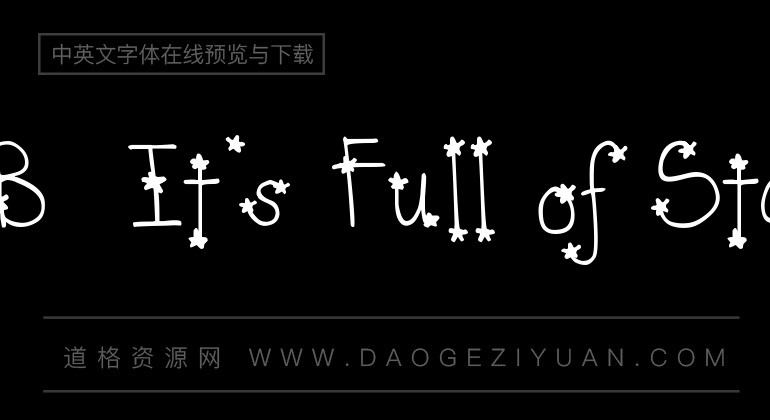
DJB It's Full of Stars
? DJB It's Full of Stars是由DJB Fonts创建的一款手写字体。它具有非常温柔而优雅的外观,适合用于精致的设计和标题。它具有易读性和可定制性,并且可以在打印和屏幕上使用。这款字体的笔画宽度和字符大小都很完美,可以让您的文字看起来更有活力。
DJB It's Full of Stars是一款非常不错的手写艺术字体,具有很好的视觉感,适合于文化类的宣传设计、商业类品牌的广告和产品包装设计以及个性化文字排版等较多场景。